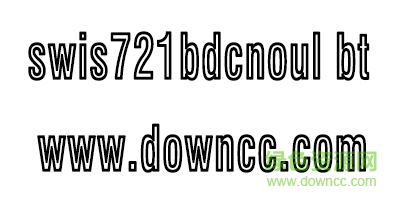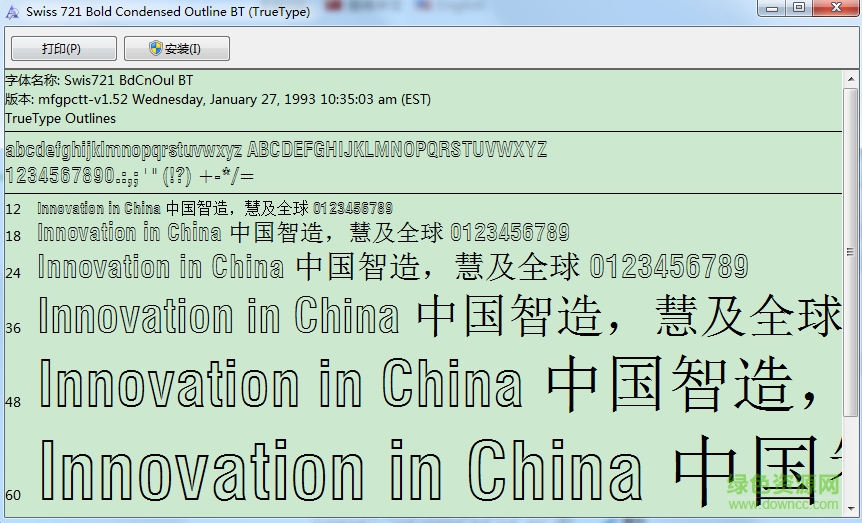
swis721bdcnoul bt字體是一款非常漂亮的英文字體,這款字體非常有特色,可以廣泛應(yīng)用于廣告設(shè)計(jì)、宣傳海報、ppt、影視制作等各個領(lǐng)域,喜歡這款字體的朋友可以免費(fèi)下載收藏喲。
swis721bdcnoul bt字體是一款極具個性的英文字體,該字體字形空心,彰顯了自己的個性,有喜歡的朋友可以來綠色資源網(wǎng)下載使用!